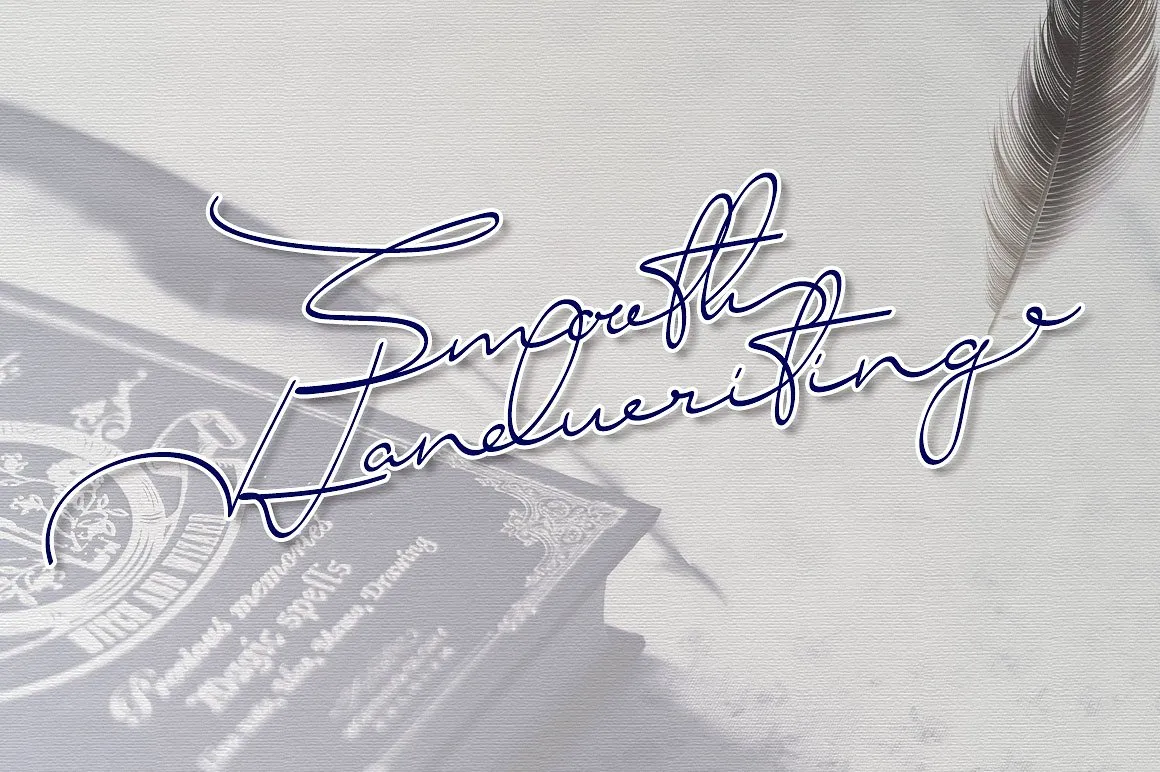
Smooth Signature Font – Download Grátis
Introduzimos a Smooth Signature Font! Esta elegante fonte de escrita cursiva foi criada pelo designer 178-MC, disponível na CreativeMarket e agora gratuita para download por tempo limitado. Seu estilo sofisticado é perfeito para assinaturas, cartas pessoais ou qualquer uso que exija um toque suave e elegante. Suavemente escrita em estilo de escrita cursiva, a Smooth Signature Font se destaca pela sua facilidade de leitura e personalização. É uma escolha ideal para aqueles que buscam criar uma assinatura única e profissional. Adorei o resultado da fonte – é perfeita para adicionar um toque sofisticado a qualquer documento ou impressão. Estamos felizes em oferecer esta font gratuitamente. Esperamos que você goste do produto!